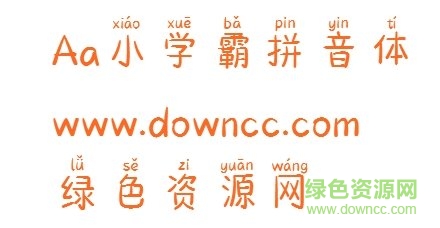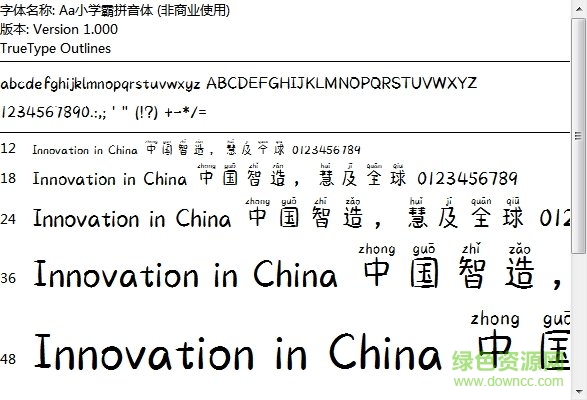
小學(xué)霸拼音體ttf文字十分清秀可人,端正簡(jiǎn)潔的筆畫讓字體效果更佳突出,字跡規(guī)整大方,有著極佳的閱讀效果,讓你眼目一新,手機(jī)閱讀起來也干呢宮頸癌舒適流暢,綠色資源網(wǎng)誠意推薦!
P.S.拼音字體存在多音字拼寫錯(cuò)誤的問題,多音字以常用音調(diào)為準(zhǔn)。
小學(xué)霸拼音體整體來說并不是很完善,部分拼音仍存在爭(zhēng)議和bug,但字形方面比較干凈清爽,喜歡這種類型的朋友可以在本站免費(fèi)嘗試哦!